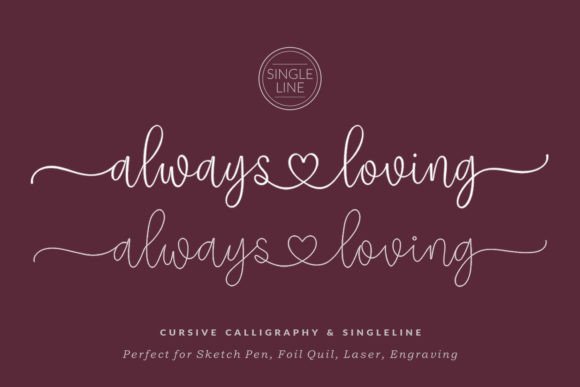
Always Loving
Jika anda sedang mencari aset berkualiti tinggi seperti Always Loving, pakej premium ini merupakan pilihan yang hebat untuk projek kreatif anda.
Dicipta dengan ketepatan, Always Loving menyediakan vektor yang bersih, tipografi yang licin dan lesen komersial untuk ketenangan fikiran.
Sama ada anda mencipta produk POD (Print on Demand), jemputan perkahwinan atau grafik media sosial, Always Loving amat bersesuaian.